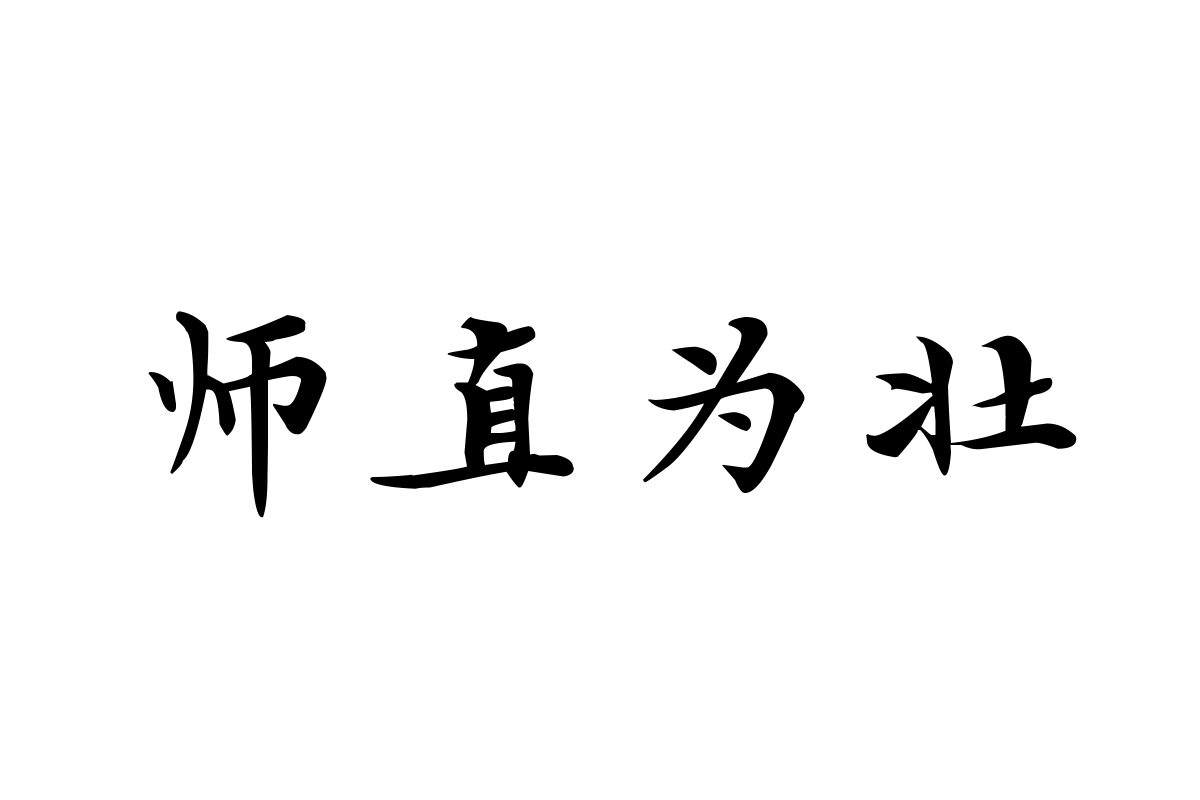
汉仪字酷堂邓氏小楷字体是一款具有独特风格的书法字体,它源自于邓氏家族的小楷书法风格。这款字体的特点是笔画流畅、线条优美,给人一种优雅、庄重的感觉。它的字形结构紧凑,线条粗细适中,既有力度又有柔美,非常适合用于书写正式文件、信件等场合。此外,这款字体还具有一定的艺术性,能够展现出书法家的技艺和个性。总的来说,汉仪字酷堂邓氏小楷字体是一款非常实用的书法字体,适合用于各种需要书写正式文件、信件等场合。